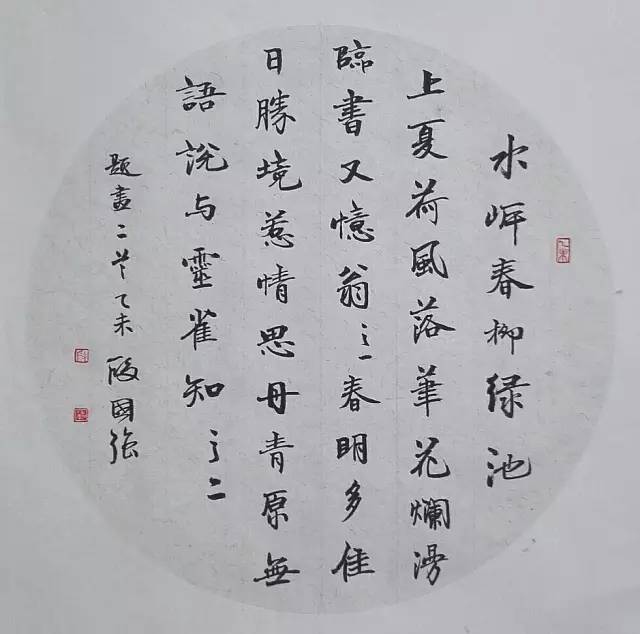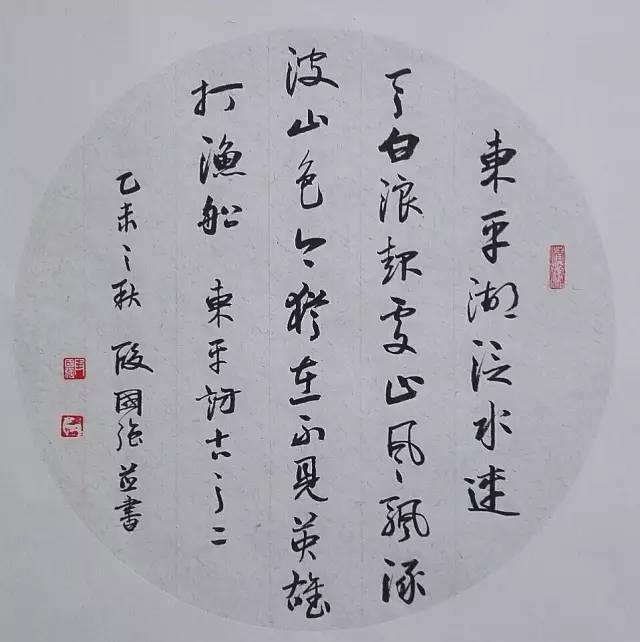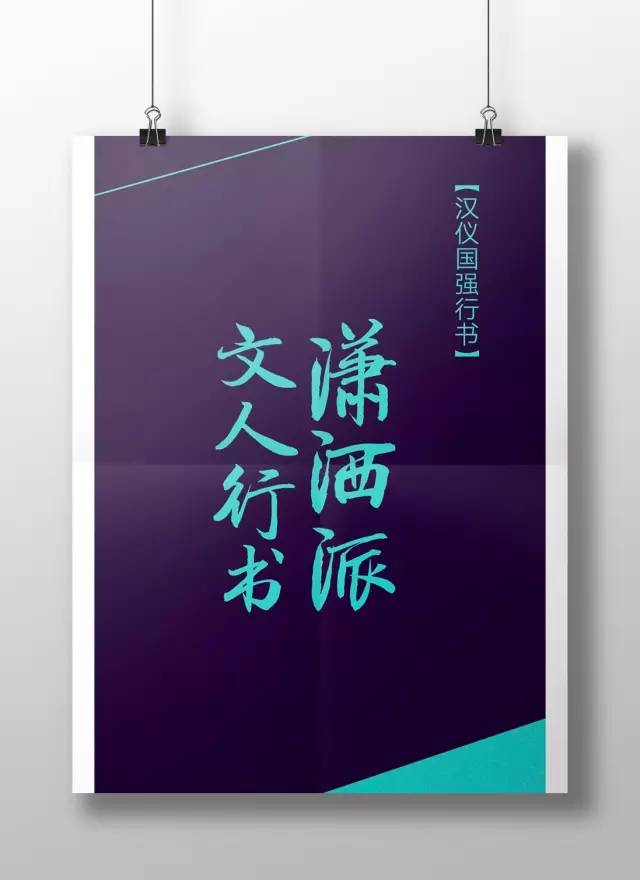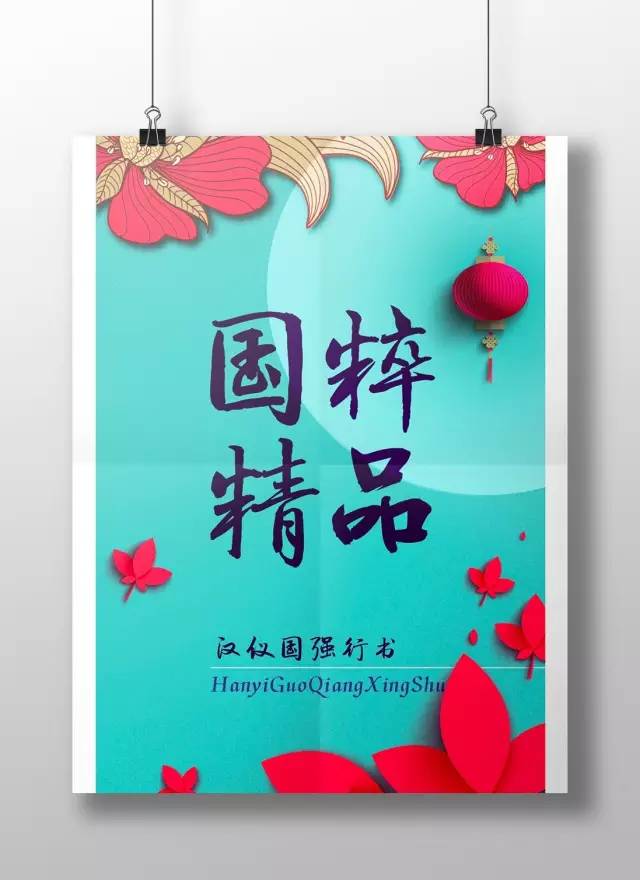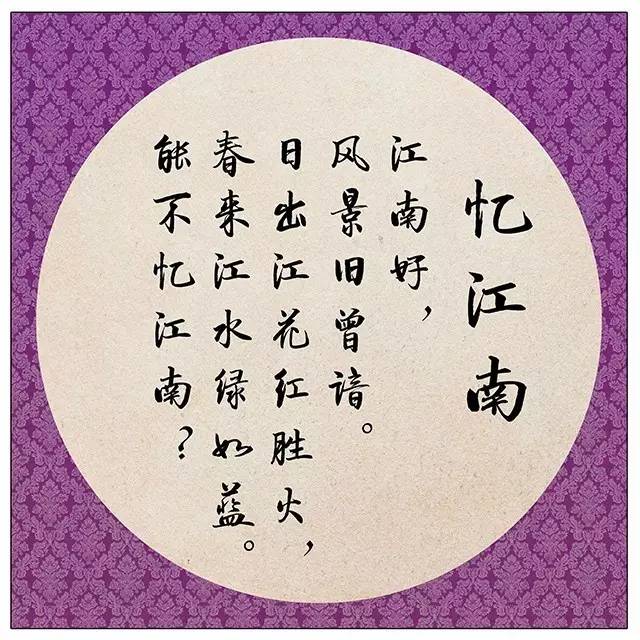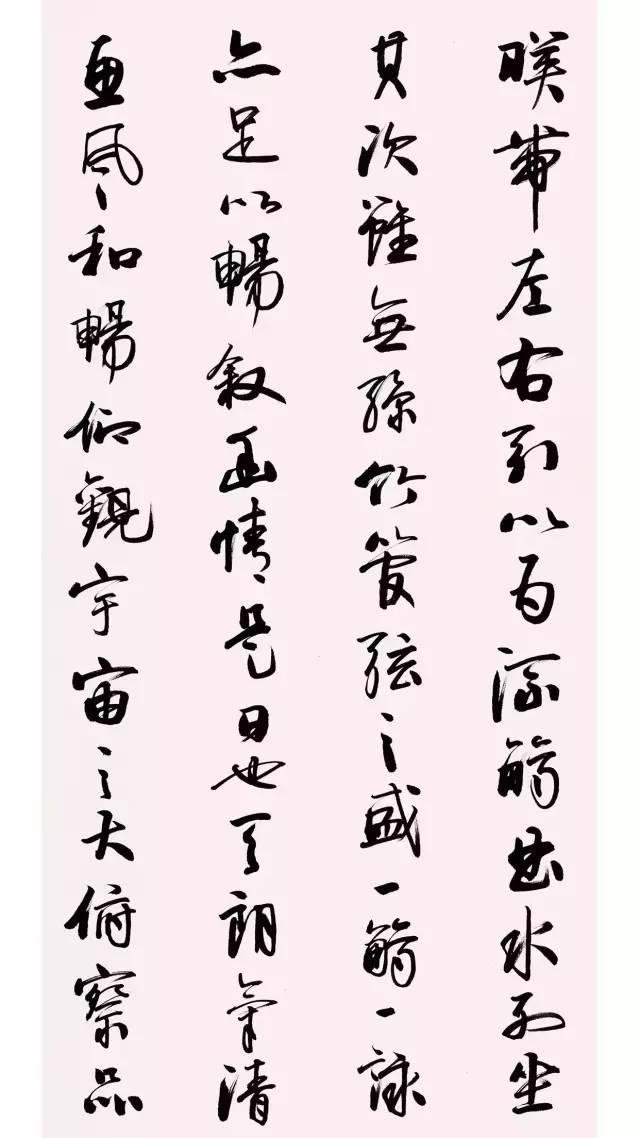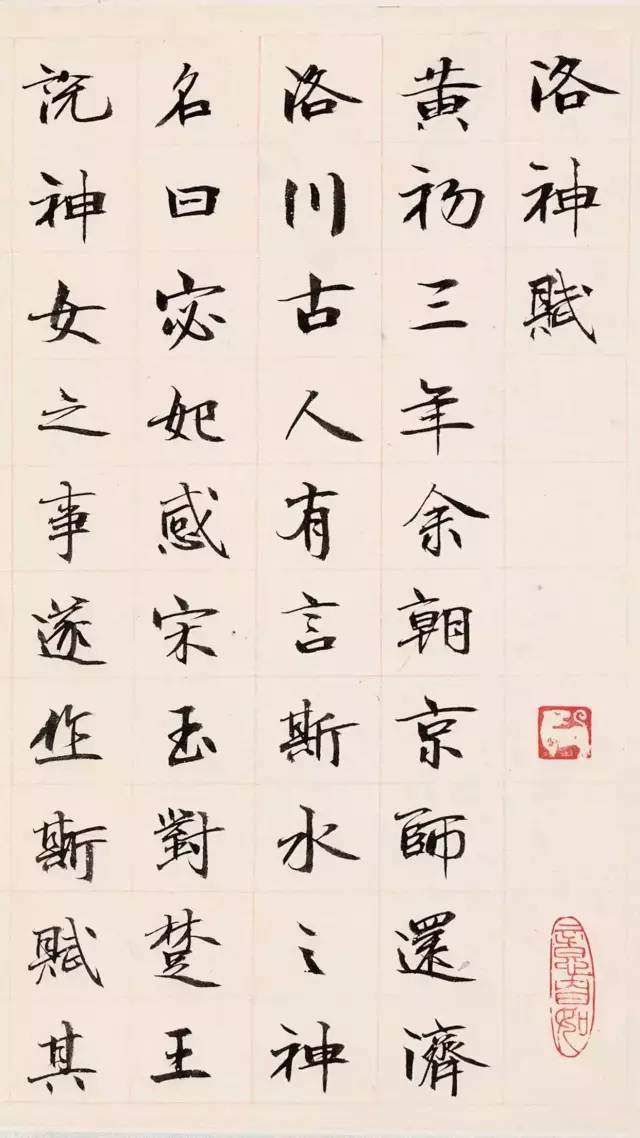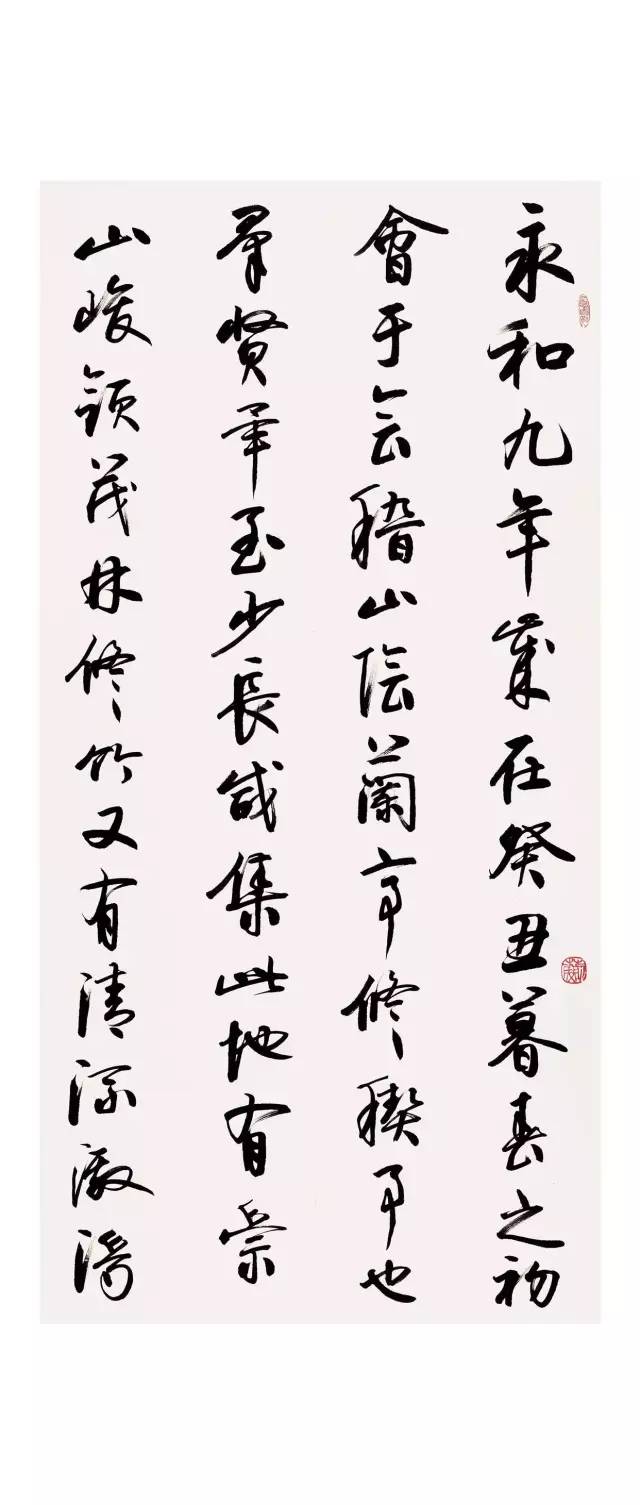
汉仪国强行书 | 汉仪国强行书字体介绍、案例
段国强
现为中国文物学会理事,对外联络工作委员会副会长兼秘书长,专家委员会委员兼秘书长。
多年从事文物研究、图书编辑工作,主编大型图书《中国文物定级图典》、《中国文物大辞典》、《中国文物鉴赏大系》、《文物名家大讲堂》、《经典中国艺术史》、《新中国捐献文物精品全集》等,入选《中国当代文博专家志》。幼习书法,从侯及名、王遐举先生学习,作品入选1-4届北京国际书法双年展,在荣宝斋(天津)、保利艺术博物馆举办书法展。
应用范围推荐:大标题/ 古籍排版/ 包装
字体气质:儒雅/ 风脉/ 侠气/ 中国风
应用环境:书籍/游戏/ 中国文化/教育/ 旅游/ 餐饮等
汉仪国强行书 | HYGuoQiangXingShu
9169字 | 中文简繁+网络字
汉仪设计团队
中文设计:马涛、刘其龙、钟宁昕
西文设计:张暄、刘嫣然
技术支持:冷怀晶、张瑶
段国强老师学习书法得益于深厚的“童子功”,曾对晋唐诸家法帖下过深功。楷书先从欧阳询入手,得其骨力,又习颜真卿丰其筋肉,还吸收了一些魏碑的字势,用笔、结字自有出处,庄重不失活跃,规矩不失灵动。特别是他的小楷,加入一些行书笔意,点画活泼中现精致,结体灵动中现规整。代表作《小楷洛神赋》,洋洋洒洒千余言,一气呵成,首尾连贯,一笔不苟,表现出深厚的传统功力。其最擅长的还是行草书,是以二王书为根基,取孙过庭《书谱》韵致、赵孟頫之妍美。平正、雍容又不失妍美、灵动的书风,显然是出自晋唐正脉,同时又吸收了元明人的姿态,化古为新。看似随意流动、潇洒中,实则笔笔精心。无论是每字的结体,还是通篇的章法布局,呼应、揖让,浓淡、黑白对比均十分讲究、妥帖。可以看出书写者在平正与险峻、唯美与古朴、圆熟与生拙间寻求着辩证与统一。他的老师王遐举先生赞之曰:“清秀之气跃然纸上。”在他的书法创作中篆隶书并不常见,但也下过功夫,隶书以《张迁碑》为体,糅以《石门颂》之飘逸,80年代王遐举就称赞:“用笔灵活,甚有功底。”篆书取《石鼓文》之质朴、浑厚,金文结体的错落、顾盼之姿,加以赵之谦的秀逸姿态,也别有意趣。观其书自有一种浓郁的古典气息,所谓“无一笔无来处”,但又非是“集古字”,分明是属于自己的“这一个”,因而既遵循书法艺术的传统美学观念,又有着清新的时代风尚。
段国强在书法上的成就,得益于多年的传统文化熏养,加之数十年不懈的笔墨追求。他长期任职于文物部门,曾经在国家文物局、中国文物报社、《文物天地》杂志、中国文物交流中心等工作,现又是中国文物学会专家委员会委员兼副秘书长,对外联络工作委员会副会长兼秘书长,从事了近30年的文物书刊的编辑工作,主编了多部大型的文物图书,如《中国文物定级图典》、《中国文物大辞典》、《中国艺术史》、《国宝》、《盛世佛光—经典中国佛教造像艺术》以及新近一出版就引起巨大反响的《新中国捐献文物精品全集》等等,其中的多种图书还获得了国家图书大奖,在业界颇具影响。他还参与了《故宫博物院藏珍品集》、《敦煌石窟全集》、《中国美术全集》等的编辑工作。编书是一种学习,编辑古代艺术史就是跟历史上最出色的大师学习,在这方面他有着得天独厚的优势。
名师的指点在段国强的学书道路上至关重要。他认为,在艺术上对他帮助最大的一是老师书法家王遐举,一是他的岳父、也是他的老师画家侯及名。王遐举先生不仅亲自指点,还在其书艺稚嫩时给予鼓励。特别是在王老身边得睹其挥毫运笔,深受启发。他认为,明清以来,诸体互参成为一种书法创新模式,但将隶书笔意完美的运用到行书中,王老为第一人,无出其右者。作为岳父的侯先生,不仅教授他书画技法,更是在学术上、做人上给予他潜移默化的影响,并一直到今天。
段国强的书法已进入了一种深谙传统又极具个人特性的阶段,难得的是其自然流露的书卷气,在当今书坛凸显个性、开张躁露的风气中别有一番韵致。对于书风的“个性”问题,他有着清醒的认识:上帝造人,每个人都是独立的个体,由于学识、修养甚至于脾气秉性的不同,每个人都有着不同的性格特点和审美趋向。放到书法上,就形成了“自家面貌”——既有平正的,也有险峻的;有温和中正的,也有躁露张狂的;有妍美清秀的,也有雄奇苍劲的。从美学上来说,不同的书风特点没有绝对的高下之分。但在学习前人的选择上,却是有着高低之别,因此,古人说“取法乎上”。如何选择师承,关乎书法今后的发展,不仅是审美问题,也是学识和修养问题。有的学书人从一开始就选择的是错误的师承,那必然要走错路,起码是弯路。有的人分不清高下,把糟粕当传统,这就不是走弯路的问题了。所以,提高修养是书法的字外功,书法从来就不仅仅是技法问题。这几年,不断有请他讲如何学习书法,他总是从古代艺术史、从书法鉴赏入手。他认为,技法是可以通过练习掌握的,而前提是审美,没有正确的审美观,熟练的技法也可能是谬误。
敬畏传统,但绝不反对创新。段国强认为,现在的问题是,不是传统已经束缚了我们的手脚,阻碍了前进的方向,而是我们对传统认识的太少,或是歪曲了传统。传统与创新绝不是对立的,历史上所有的具有创新精神的书法家都是优秀的传统继承者,从王羲之、王献之到颜真卿、柳公权,从米芾、黄庭坚到赵孟頫、董其昌,无不如是。所有真正意义上的创新均应是符合艺术规律、符合时代发展的,经过艺术家长期提炼的高等艺术,要经过艰苦的磨练,又是水到渠成的。任何走捷径、异想天开闭门造车式的“创新”,只能是离真正的创新越来越远。
段国强作品欣赏
《洛神赋》节选
兰亭序